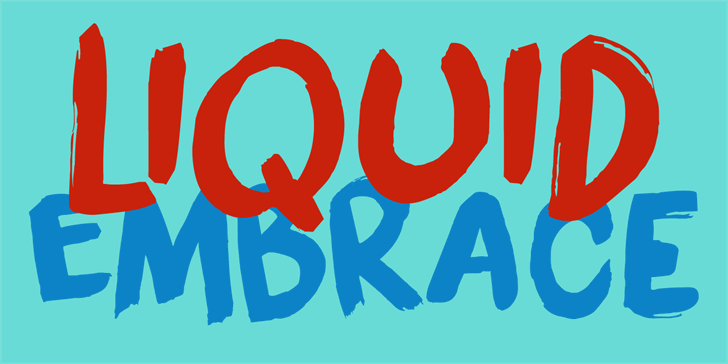
DK Liquid Embrace é uma fonte script criada por David Kerkhoff no ano de 2015. Esta é a versão básica, ou demo, do famoso “Liquid Embrace”. Disponível gratuitamente apenas para uso pessoal, se você pretende usá-la em projetos comerciais, recomenda-se adquirir sua versão completa. A fonte full inclui as opções de calibre e direcionamento, direitos de embutimento, além dos caracteres extras encontrados na sua página oficial: hanodedfonts.com. Não use essa font no desenvolvimento de jogos, aplicativos ou softwares. Se você precisar de uma licença para esses usos específicos, visite nossa página www.hanodedfonts.com. A DK Liquid Embrace é perfeita para incorporar em projetos que valorizam a personalidade e o estilo único do design tipográfico.